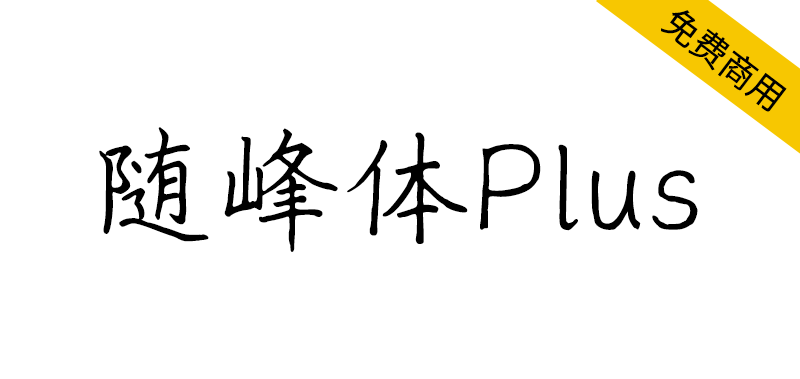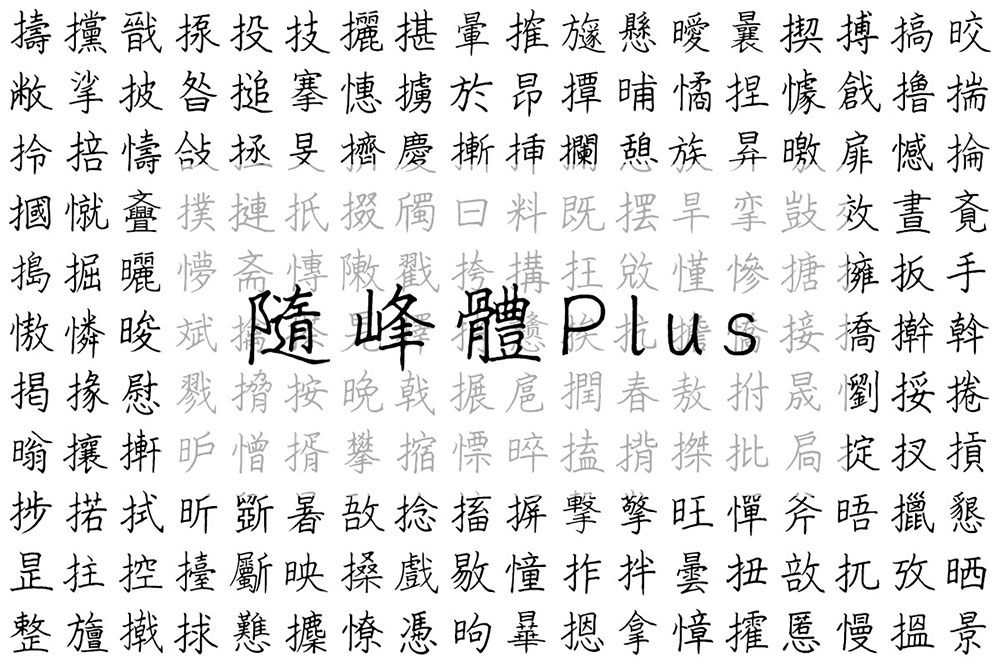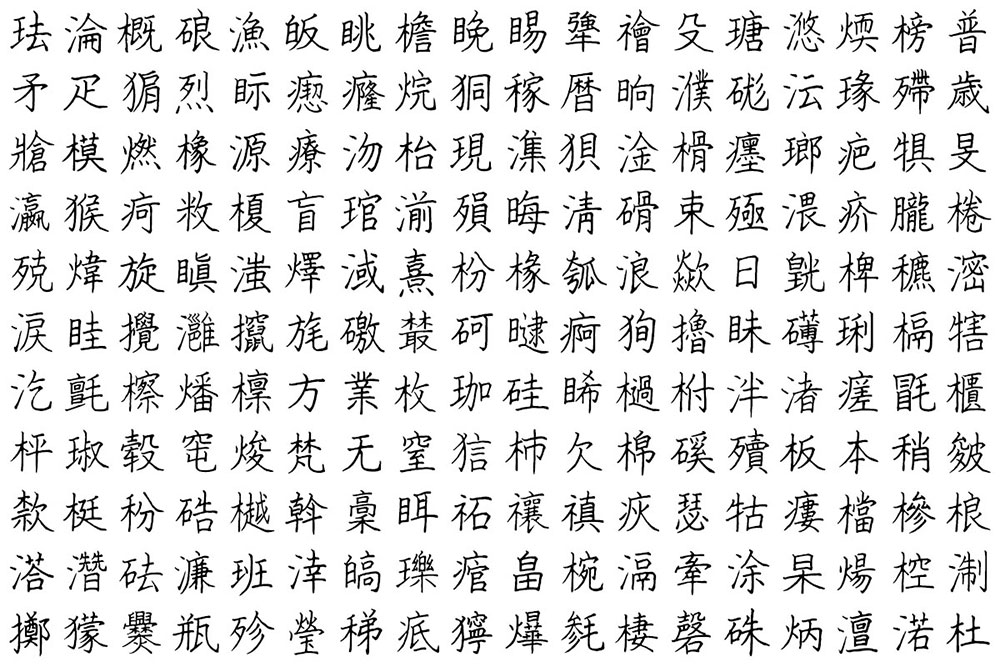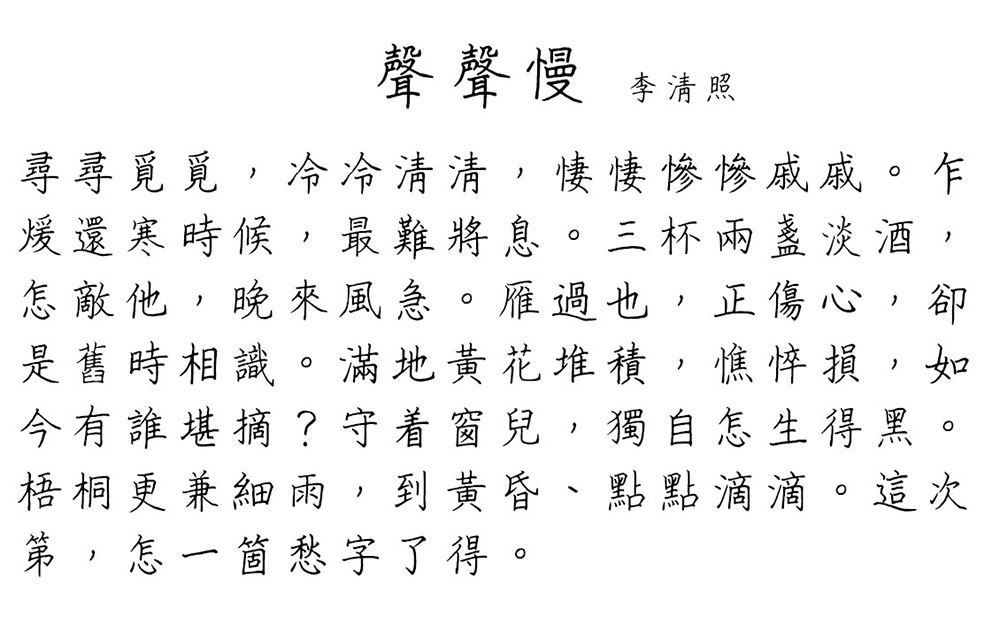
「随峰体」是创作者阿坤的手写作品,是我们cjkFonts 在2022年公开的开源字形,不但免费,更可供个人及商业使用,回馈开源社群。
「随峰体」自推出后大受欢迎,不但应用很广,还有多个衍生创作版本。当中最大型的,有晓声通秋茄体,增补了《国语辞典》(包括《简编本》、《重编本》、《成语本》)中所有用字,补充至逾15000字。同时亦有其他补充和修改「随峰体」字形的版本。
为方便「随峰体」的使用者,我们cjkFonts 的字型设计师以「随峰体」原档案为基础,整合不同的衍生版本,并再添补和修订使用者有需求的字,把新制作成果发布作「随峰体Plus」。除了原来的「随峰体」外,「随峰体Plus」也以开源字型一并发布,免费提供及每位使用者作各种个人及商业使用。